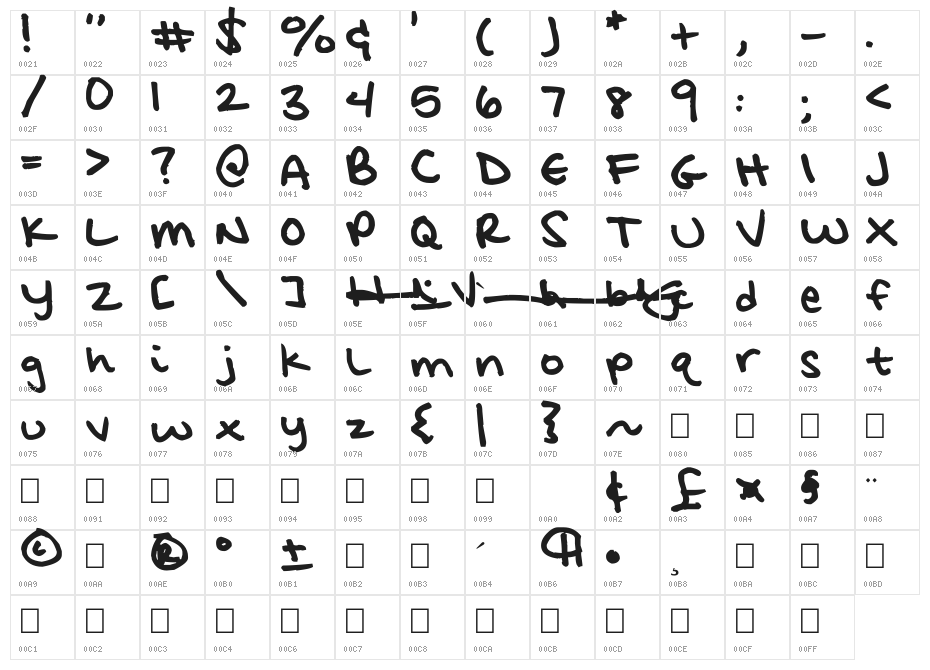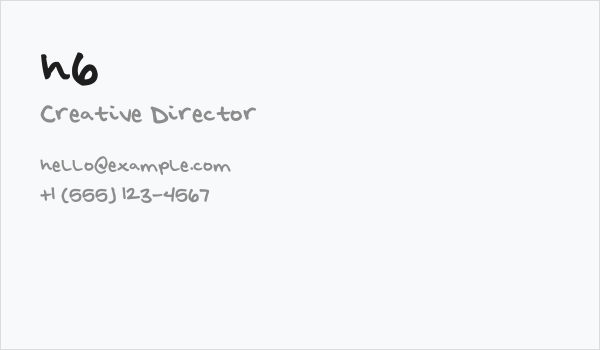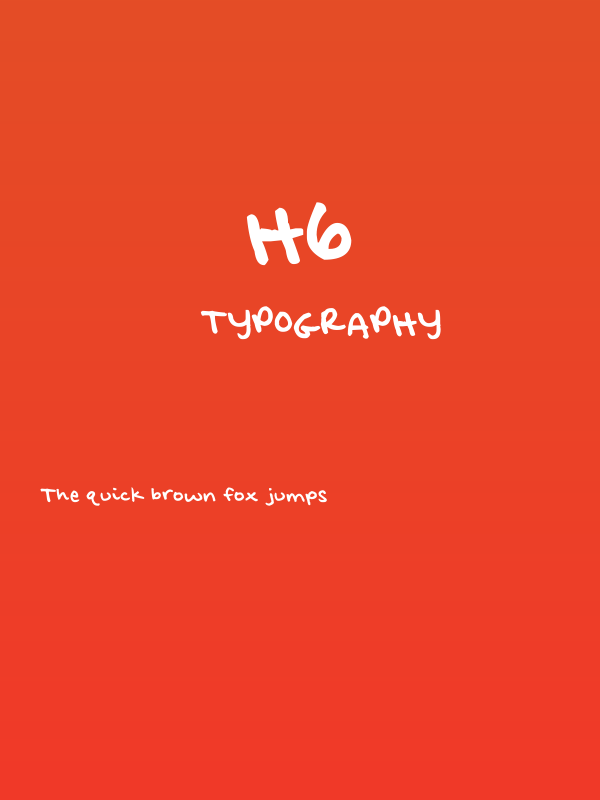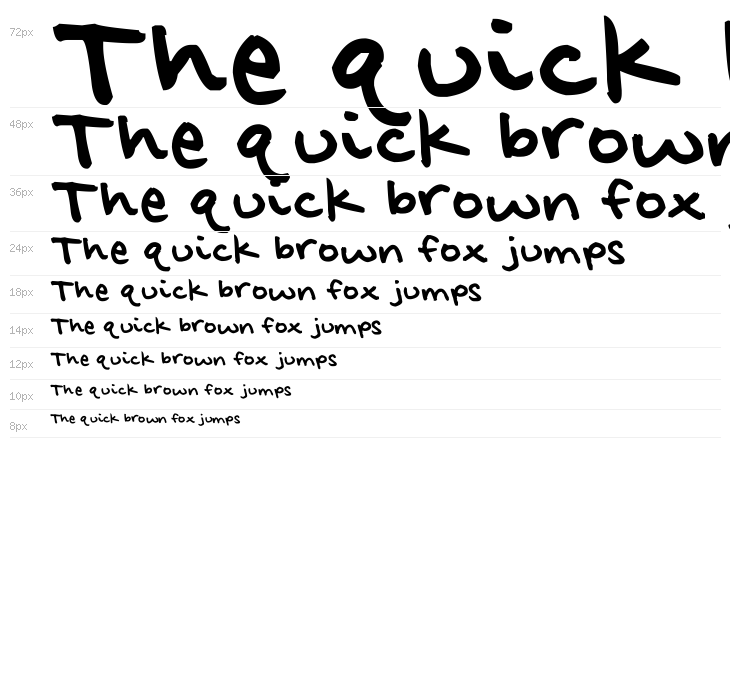
h6 Font
| Stile generale | Playful, Informal, Casual |
| Caso d'uso | Headlines, Logos, Informal text |
| Progetti proposti | Children's books, greeting cards, creative branding, personal blogs, and informal invitations. |